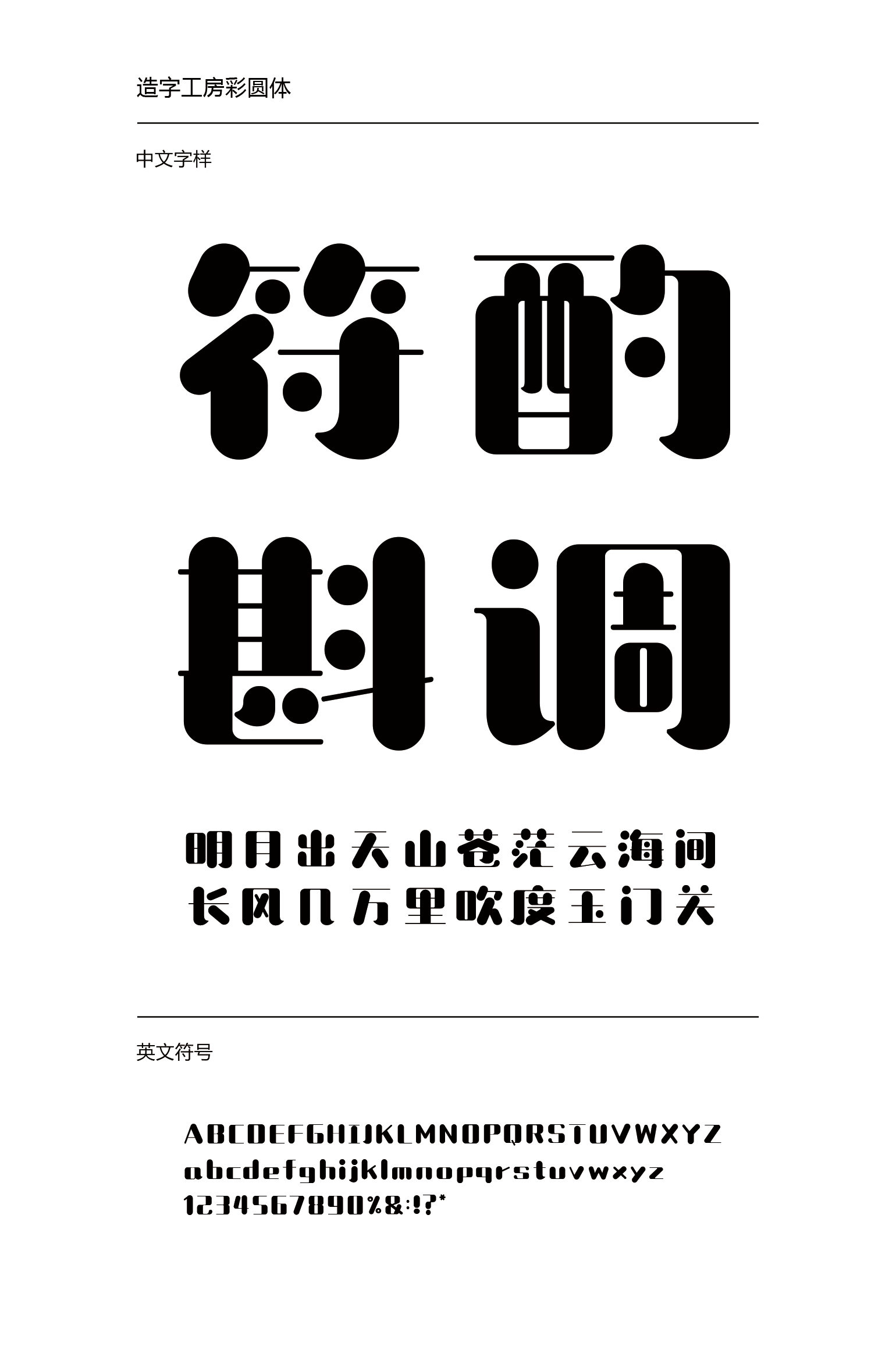
造字工房彩圆体
造字工房彩圆体设计说明
造字工房彩圆体,其字形丰腴圆润、体势柔萌,笔画粗细对比强烈,自然舒展。风格天真活泼,卡通可爱。此款字体适用于儿童读物、报刊杂志标题、广告设计等视觉环境,有着极强的应用空间。本字体为简体字库,采用OpenType/CID格式,Adobe-GB1-5编码。基于中华人民共和国GB2312-80字符集标准,另按需添加101个汉字。共收容字数6864CJK汉字,ASCII常用字符100个。